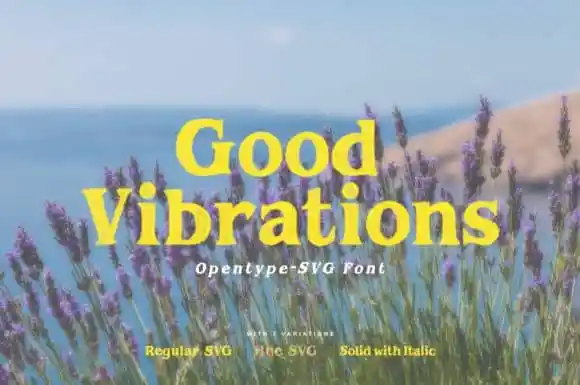
A Good Vibrations Serif Font é uma escolha perfeita para designers que buscam um estilo elegante e sofisticado. Esta serif font foi cuidadosamente criada pelo designer Ryn Pojas, utilizando apenas black ink e um pincel de esclera bem-used. O resultado é uma tipografia versátil e resistente, que se destaca tanto em tamanhos grandes quanto menores. Embora seja simples e neat, a Good Vibrations Serif Font oferece um acabamento único, com uma sensação muito humana e texturada. Suas linhas finas e suaves, bem como o contraste entre as letras de fundo e os traços superiores, permitem que seja facilmente adaptável a diversos projetos. É perfeito para aqueles que valorizam estilo e precisão em sua fonte escolhida. Sua versatilidade faz com que ela se destaque quando adotada em uma ampla gama de ideias criativas, tornando-as mais chamativas e memoráveis. Seja você um designer gráfico ou um fotógrafo, a Good Vibrations Serif Font pode ser o toque final necessário para sua próxima produção visual.